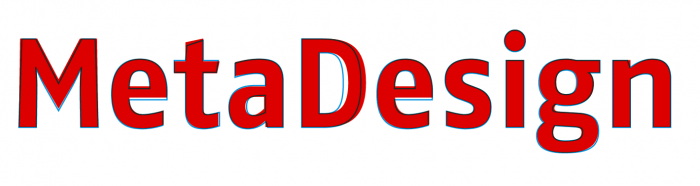
Logo MetaDesign
Danke für das Feedback, aber für mich ist es offensichtlich das es keine Fargo ist.
Die Schrift ist näher an der Ciutadella als an der Fargo.
Danke für das Feedback, aber für mich ist es offensichtlich das es keine Fargo ist.
Kannst du das auch begründen?
Wie Stefan schon sagt: es wird eine für den Logo-Einsatz leicht modifizierte Fago sein. An einigen Buchstaben, wie dem M hat man deutlich geschraubt, an anderen wie dem s überhaupt nicht. Die Ciutadella hat komplett andere Buchtstabenformen und ist aus einer komplett anderer Schriftstil-Kategorie. Ist mir schleierhaft, warum du diese ins Spiel bringst.
Hier das Logo nochmal in groß:
Danke für die Aufklärung, das M hat mich stark an eine DIN oder Ciutadella erinnert.